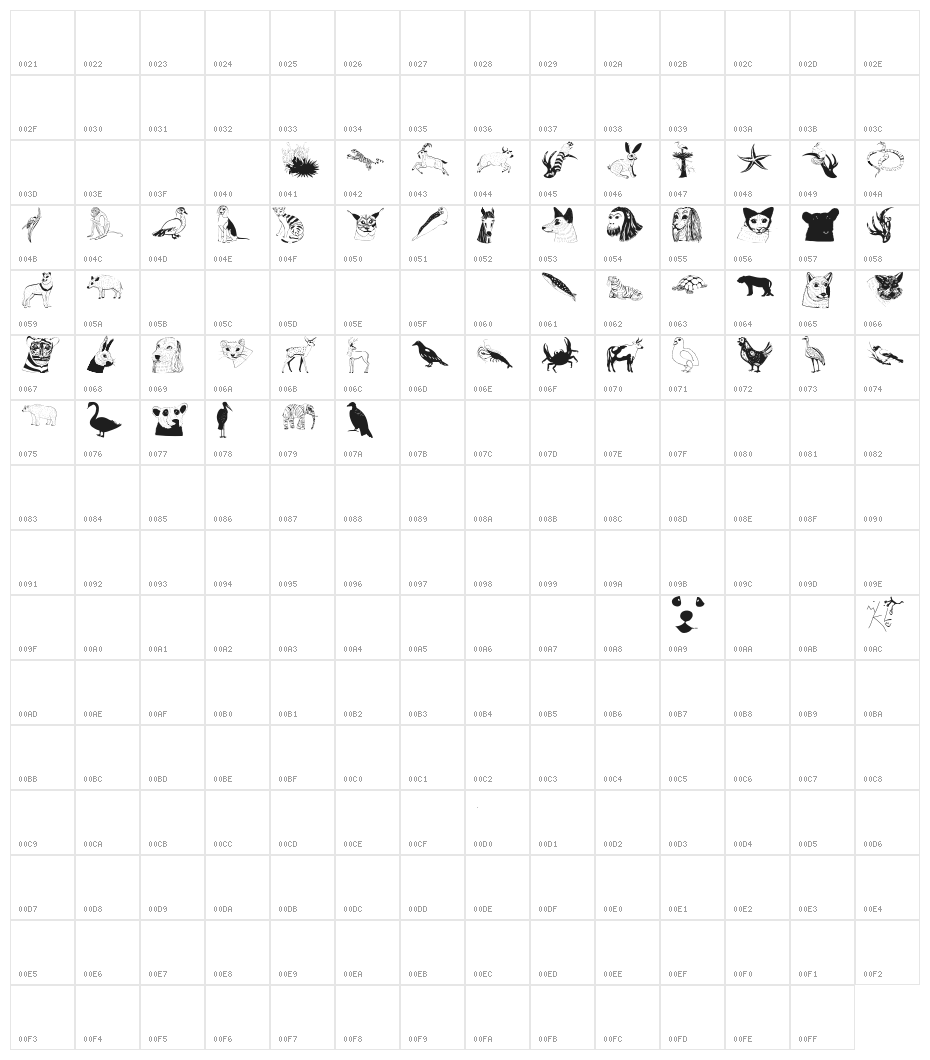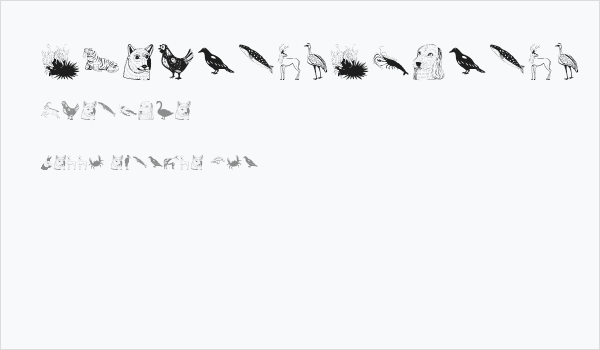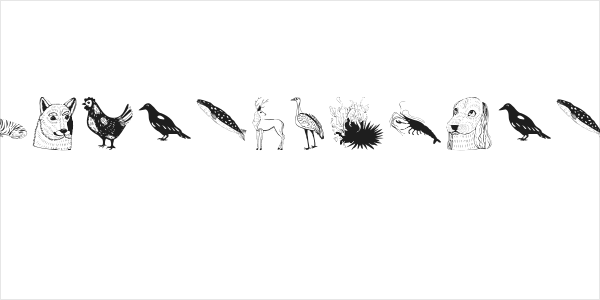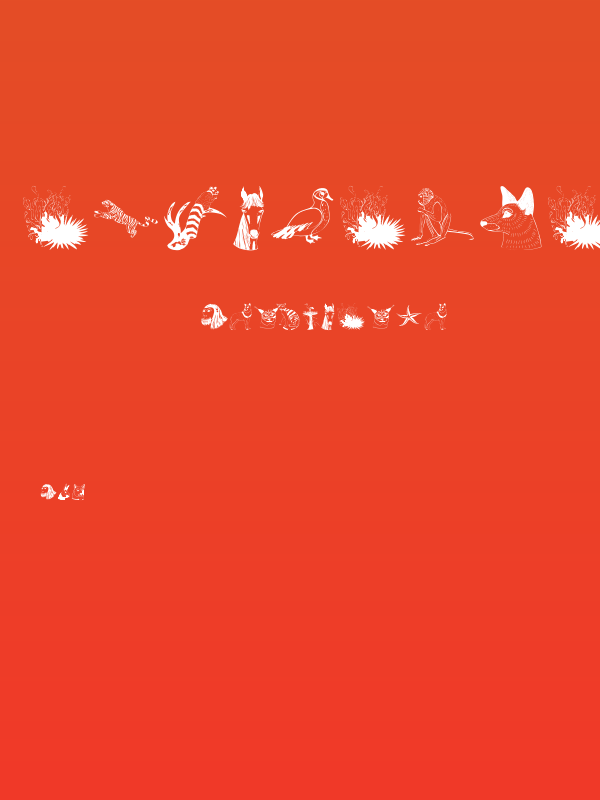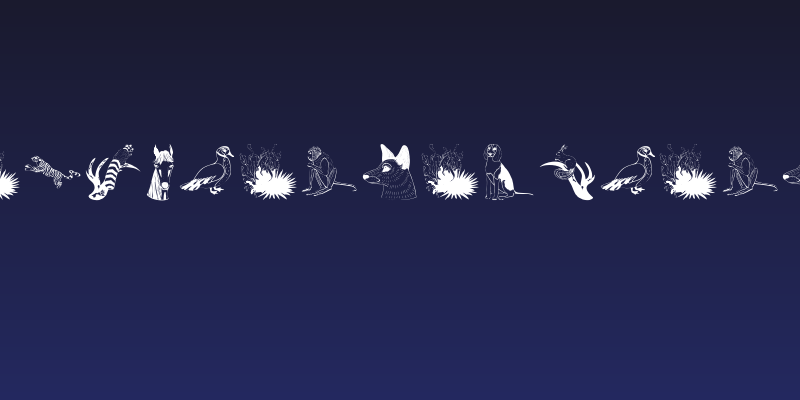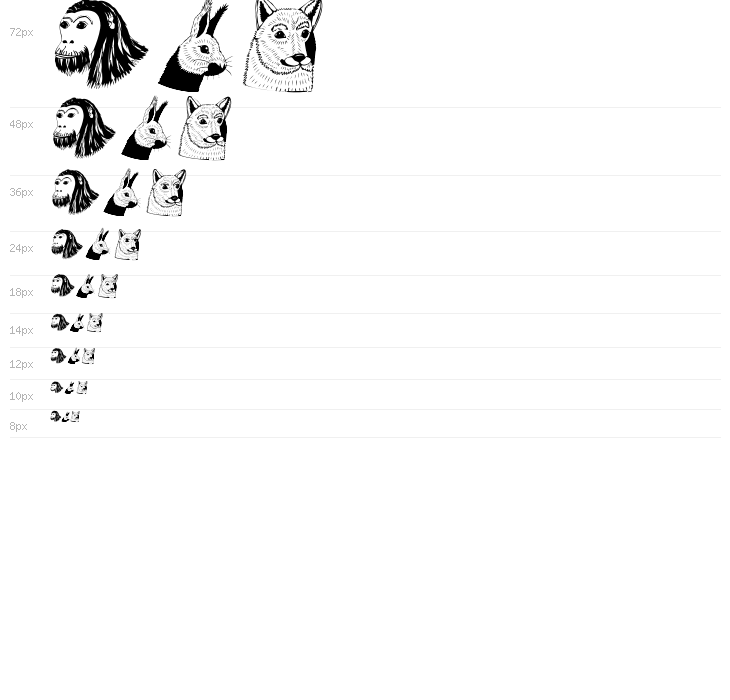
AbermalsAnimals Font
| Gesamtstil | Decorative, Whimsical, Hand-drawn |
| Anwendungsfall | Display, Posters, Themed projects, Educational materials |
| Vorgeschlagene Projekte | Children’s books, educational materials, animal-themed posters, playful branding, creative invitations. |